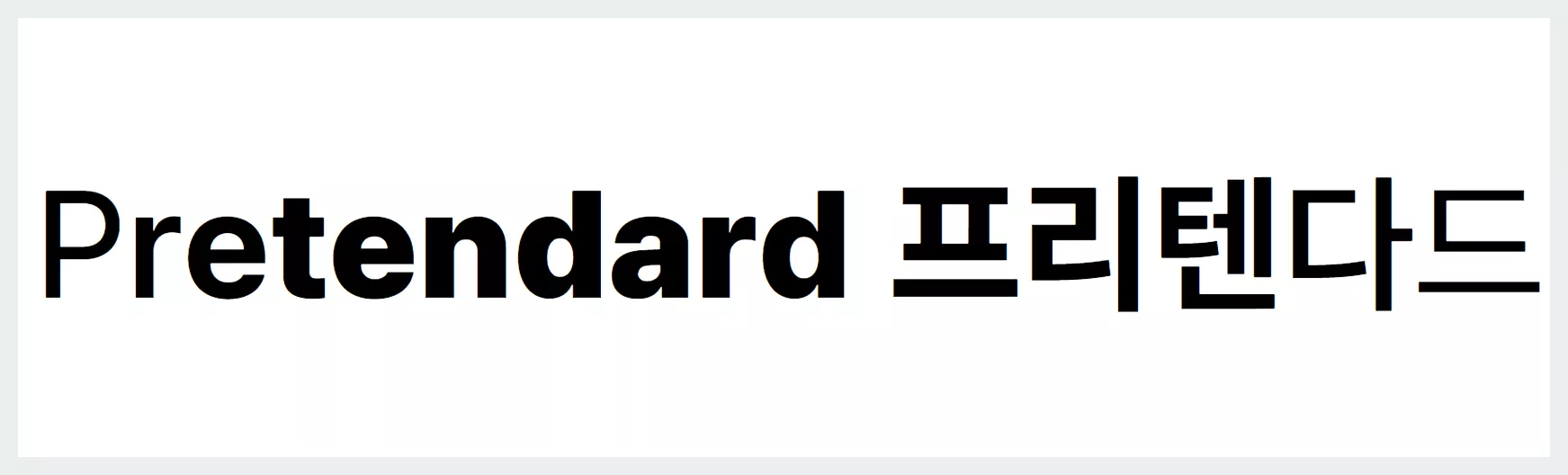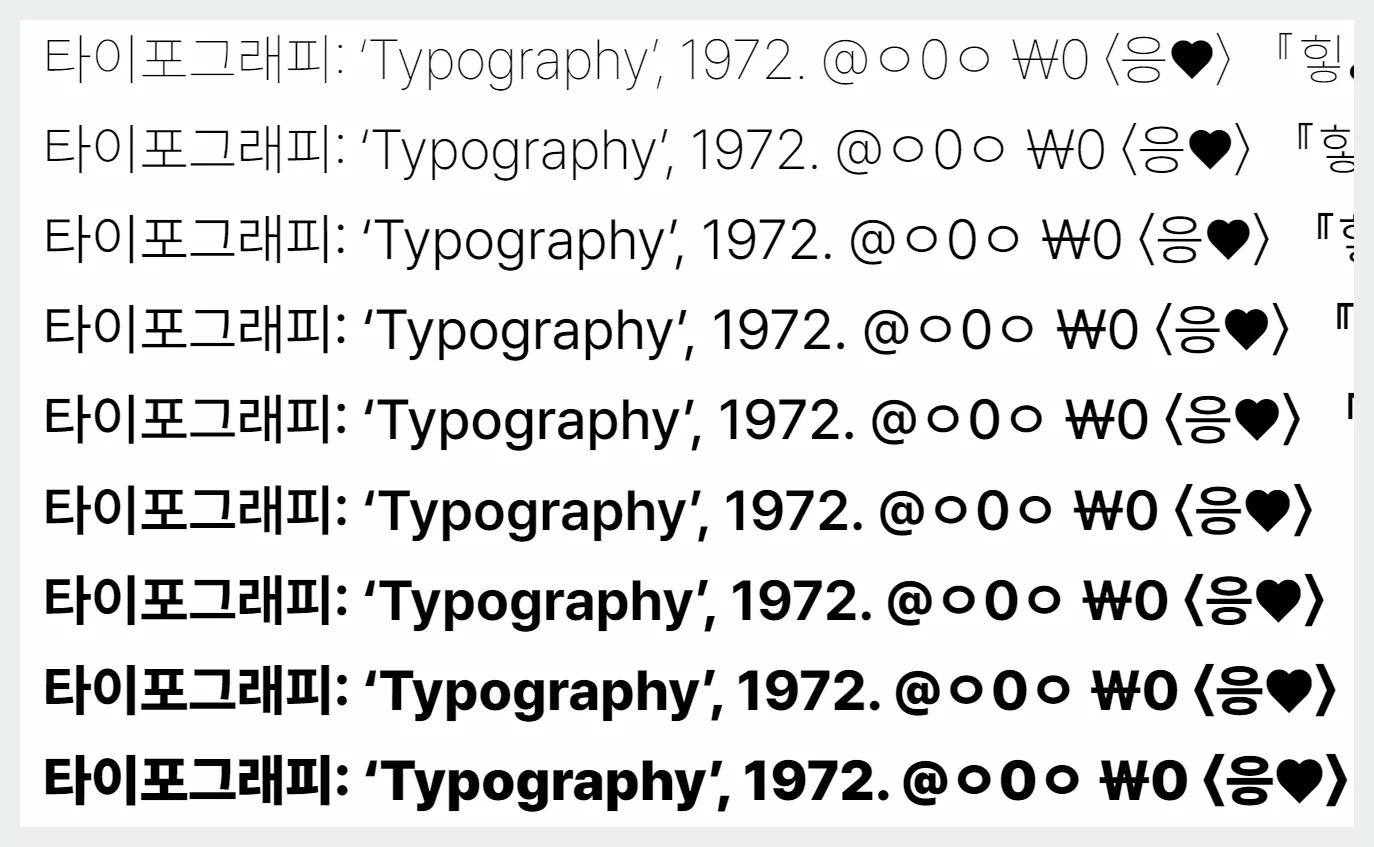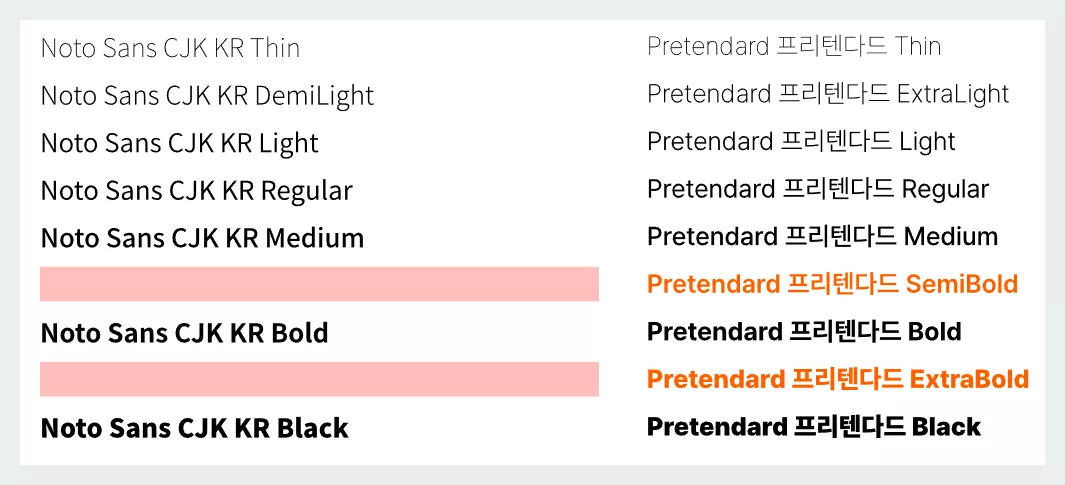
프리텐다드 Pretendard 폰트란?
프리텐다드는 네오 그로테스크 스타일의 서체로, 깔끔한 디자인과 높은 가독성을 자랑합니다. 본고딕(Noto Sans)과 Inter 서체를 기반으로 제작되어 156개 이상의 언어를 지원하며, 9가지 굵기를 제공해 다양한 디자인 요구를 충족시킵니다.
프리텐다드의 특징
- 다국어 지원: 한글, 영어를 포함한 156개 언어를 지원.
- 가변 폰트 기술: 두께를 자유롭게 설정 가능.
- 다양한 플랫폼 호환성: 웹, 모바일, 인쇄물 등 모든 플랫폼에 적합.
마무리하며